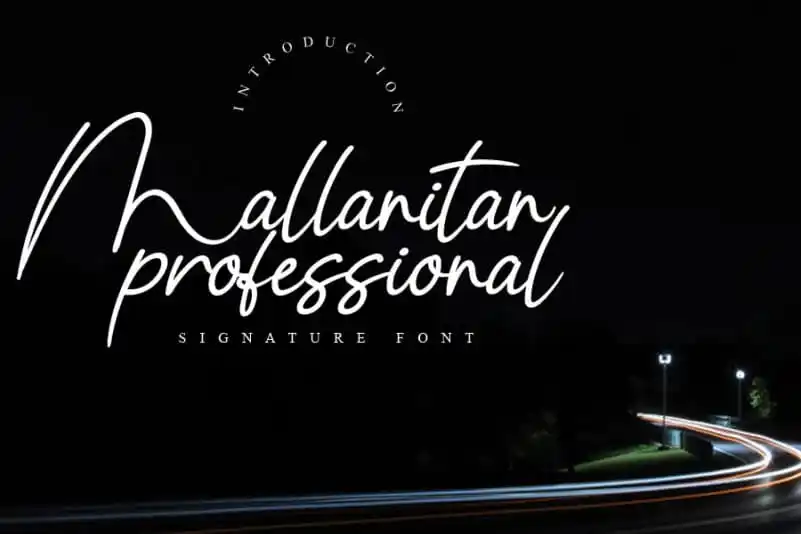
Mallanitan Handwritten Font – Download Grátis
A Mallanitan Handwritten Font é uma opção única e simples para aqueles que buscam algo elegante e descontraído no design do papel. Este font foi criado para quem ama a simplicidade, mas também valoriza personalização e detalhes delicados. Perfeito tanto para criações de eventos sociais como casamentos, quanto para arte de estacionamento e posts em redes sociais. Com sua elegante e versátil escrita livre à mão, você terá o prazer de criar mensagens memoráveis que destacam a personalidade do seu evento ou projeto. Este font é uma ótima maneira de dar um toque único ao seu design, seja para cartas de casamento sofisticadas ou postagens em redes sociais impactantes. Além disso, o Mallanitan Handwritten Font é perfeito tanto para profissionais que buscam agregar detalhes especiais a seus trabalhos quanto para designers criativos que desejam explorar uma expressão mais delicada e pessoal. Ele adiciona um toque autêntico e único a qualquer projeto onde você quiser exaltar sua individualidade.